Шрифт як мистецтво
Кому не доводилося із захопленням спостерігати за роботою художника, як з під його руки з'являлися красиві літери. Так хочеться опинитися на його місці, але перші практичні спроби, як правило, охолоджують запал. Все виходить криво, неакуратно, фарба лягати нерівними плямами, розпливається. У чому ж справа?
Зазвичай ощибки відбуваються через незнання найпростіших закономірностей і прийомів шрифтової роботи.
Найдавніший український шрифт - устав. Їм написані найдавніші пам'ятки писемності, в тому числі Остромирове Євангеліє (1056-57). Це стиль повільного, спокійного листи, природний в той час, коли потреба в книгах була ще невелика і переписувалися вони в монастирях. Букви тут важкі і незграбні, розставлені рідко, просторо.
У XIV столітті виникає полуустав. В цей час зростає потреба в книгах. Тепер їх переписують професійні писарі. Шрифт набуває швидкість і розмашисто, літери стають дрібніше, вони помітно спрощуються.
Подальший розвиток листи призвело до виникнення скоропису, яка зустрічалася спочатку в документах, листах, а пізніше в книгах. Пишного майстерності досягла вона в xVII столітті - це справжнє каліграфічне мистецтво. В середині XVI століття з'явилися книги, набрані першим українським друкарським шрифтом, який відтворював найбільш поширений шрифт рукописних книг того часу - полуустав.
Створення нового, цивільного шрифту стало одним з найважливіших заходів Петровської епохи. Новий шрифт був чіткий, округлі, світлий, ясний і раціональний. Діловитість в ньому явно переважала в порівнянні зі старомодним декоративним напівстатутом.
Щоб в подальшому були зрозумілі окремі терміни і позначення, розглянемо деякі букви алфавіту і окремі елементи, з яких вони складаються.
Зверніть увагу на таблиці шрифтів. При всій несхожості у букв в конструкції багато спільного. Всі вони складаються з основних - вертикальних і додаткових сполучних - горизонтальних і похилих штрихів. У шрифтах типу антикви важливим елементом є зарубки - короткі горизонтальні і вертикальні лінії на кінцях основних або сполучних штрихів. Простір, укладену між основними штрихами, називається внутрібуквенним просвітом. Відстань між сусідніми буквами - межбуквенное просвітом. Залежно від відносини між толщінкамі основного і з'єднувального штрихів, від наявності і форми зарубок шрифти можна розбити на п'ять основних груп:
- Контраст між основним і сполучними штрихами помірний (1: 3). Зарубки невеликі з заокругленням на кутах
- Контраст великий (1: 5). Зарубки довгі і тонкі
- Контраст невеликий (1: 2). Зарубки майже прямокутної форми
- Контраст майже відсутня, зарубки нагадують бруски зазвичай прямокутної форми (бруски шрифти)
- Контрасту майже немає. Зарубки відсутні (рубані шрифти)
Букви алфавіту діляться на симетричні і асиметричні.
Симетричні - А Д Ж І Л М Н О П Т Ф Х Ц Ш
Асиметричні відкриті вправо - Б В Г Е К Р И Т А Ю
Асиметричні відкриті вліво - З У Ч Е Я
Полуторні - М Ж Ш Щ Ю И
Ці особливості варто враховувати при розмітці слів, рядків для врівноваження межбуквенних присвятив, тому що асиметричні букви створюють в них порожнечі.
Важливе значення має правильний вибір матеріалів та інструментів, а також послідовність виконання роботи. Слід взяти якісну, добре проклеєну папір. Вона не повинна мати подряпин, вдавлень. Бажано спочатку перевірити як лягають на неї фарби і туш, ворситься вона при роботі гумкою.
З фарб зазвичай використовують гуаш, туш чорну (кольорова лягає нерівними плямами), іноді акварель.
Одним з основних інструментів для виконання мальованих шрифтів є кисті колонкові і білячі, як плоскі, так і круглі. Також використовуються плакатні пір'я, скляні трубочки і спеціально заточені палички з твердого дерева. Цими інструментами можна писати не тільки тушшю, але і фарбами. Але фарби не повинні бути густими.
На робочому місці в своєму розпорядженні: лінійку, кутник, заточені прості олівці середньої твердості (ТМ, Т), невеликі кисті, ручки з пір'ям, скляні трубочки (рейсфедери), туш, баночку з водою, ганчірку для протирання інструментів, кілька аркушів паперу.
Туш бажано налити в кришечку від флакона або іншу невелику ємність, під яку покладіть шматок будь-якого паперу (щоб не бруднити стіл).
На першому аркуші випробуємо інструменти. Кожним з них проведено різноманітні лінії:
прямі - вертикальні, горизонтальні і похилі
округлі - хвилясті, звивисті
Щоб кисть і перо добре набирали фарбу їх спочатку потрібно сполоснути у воді і злегка протерти ганчіркою. Також потрібно через 10-20 хвилин роботи промивати у воді і начисто протирати інструменти. Тоді вони будуть давати чітку без помарок лінію.
Особливою підготовки вимагають скляні трубочки. Спочатку злегка загинають тонкий кінець трубки, розігрів його на вогні сірники. Отвір при цьому може заплави, після охолодження вигнутий кінець поточити на дрібному бруску або наждачним папером, поки слухавка не буде продуватися.
Наповнюють трубку фарбою так: широку частину беруть в рот і, опускаючи тонкий кінець в фарбу, злегка вдихають в себе, туш піднімається в трубці. Давши лишків фарби стекти, приступаємо до роботи. Трубку бажано тримати покруче, тому що в положенні, близькому до горизонтального, фарба може витекти. Те ж може статися при затримуванні трубочки в одній точці.
На іншому аркуші, разметив олівцем рядки висотою 1-2 см. Для вправ пір'ям "редис" і трубочками і висотою 4-5 см. Під плакатне перо тренуємося в написанні елементів букв.
Пишемо по рядку основних штрихів як із зарубками, так і без них, похилих і округлих деталей букв.
Рука з незвички швидко втомлюється, тому робимо паузи. Іноді від сильного напруги вона починає тремтіти. Чи не стискувати занадто сильно перо, розслабте пальці. Можна повернутися до першого аркушу вправ, помалювати вільно розташовані лінії. Це позбавить руку від скутості. Перший час при проведенні вертикалей ми мимоволі завалюємо їх трохи вліво або вправо. Для самоперевірки намітьте за допомогою кутника кілька вертикальних ліній.
Нарешті ми можемо зайнятися головним завданням - вивченням і написанням букв.
Виберіть шрифт простіше. Почніть з букв, подібних за накресленням: Г Е Н П Т Ц Ш Щ. Дані знаки складаються з прямих основних і сполучних штрихів. Розмітьте кожну букву. Зверніть увагу, що додаткові штрихи у Н і Е розташовані трохи вище середини. Старанно не поспішаючи пропишіть їх інструментом, яким володієте впевненіше. Це зовсім не виключає використання інших інструментів. Де необхідно в хід йдуть і скляні рейсфедери, і різної ширини плакатні пір'я.
Для заправки кутів і зарубок використовуємо тонкі кисті, звичайні учнівські або креслярські пір'я.
Потім розмітьте інші літери, нарощуючи ступінь складності. Напишіть знаки з переважанням похилих елементів - А Д Л У М Х І Ж К, потім з напівкруглими елементами - Б В З Р Ф Ч Я, завершите буквами округлого накреслення - О С Е.
Закінчивши, уважно огляньте зроблене, проаналізуйте помилки, де потрібно білилами, лезом або гострим ножем приберіть затекло фарби, інші помарки. Добре якщо ви вивчите кілька різновидів шрифтів і потренуєтеся в їх написанні.
Звичайно для успішної роботи потрібен певний навик, практичний досвід. Тому починаючому шрифтовика не слід впадати у відчай у разі невдачі :)
Послідовність прокладки ліній великих літер рубаного шрифту
Вказана послідовність прокладки ліній рубленого шрифту пером, пензлем або трубкою. Одним рухом скляної трубки рідко вдається прокласти рівну, правильну лінію. Тому напис, зроблений трубкою, доводиться поправляти пензлем, а іноді і підчистити. Незважаючи на це, робота трубкою має велику перевагу: трубку або перо можна вести, майже не відриваючи від паперу, що значно економить робочий час. При відомій навичці можна викреслювати одним прийомом також півкруги і похилі лінії букв.
Розмітка шрифту при роботі трубкою спрощується: в даному випадку достатньо буде провести дві горизонтальні лінії, що обмежують висоту букв, і поставити крапки на верхній горизонталі, що вказують ширину букв, проміжки між ними і відстань між словами.
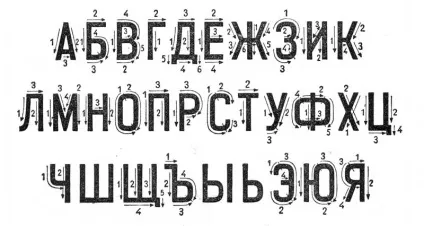
Техніка виконання рубаного шрифту універсальним плакатним пером
Послідовність прокладки ліній великих літер рубаного шрифту
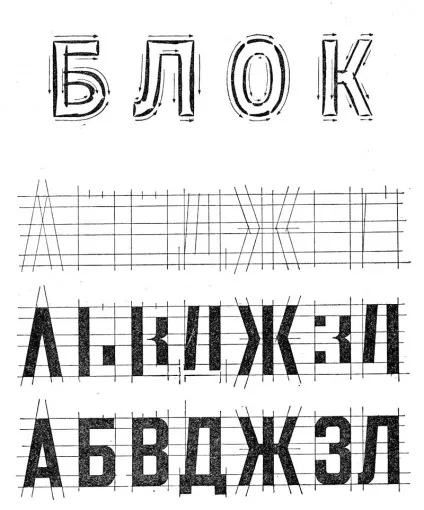
Шрифт, виконаний шірококонечним пером
Стрілки - напрямок штрихів. Цифри - послідовність